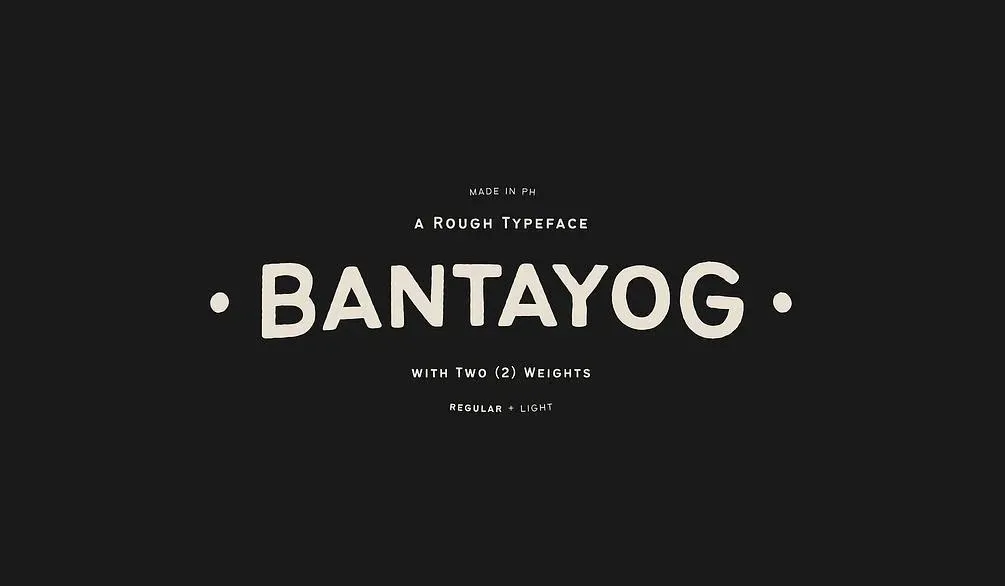
A fonte ‘Bantayog Font’ é uma exuberante escolha para qualquer projeto que busque trazer a essência da história filipina à vida digital. Inspirada no formato de um velho livro de fósforos, foi criada por John David Maza em 99designs como uma fonte Display. Com uma aparência robusta e em maiúsculas, remete diretamente para o tipo clássico encontrado nos monumentos históricos filipinos que narram fatos importantes da passada e biografias de figuras nacionais. Esta fonte oferece um toque nostálgico e autêntico à sua criação, combinando uma tipografia livre com elementos de tipo em maiúsculas robusto. Perfeita para textos como gravações históricas em monumentos, ou mesmo para criar um estilo único e memorável no design de logotipos ou rótulos em ambientes que valorizam a história do seu país. Bantayog não apenas celebra a riqueza cultural da Filadélfia, mas também oferece aos designers uma maneira única de preservar esses valores através dos olhos da nossa tipografia moderna.